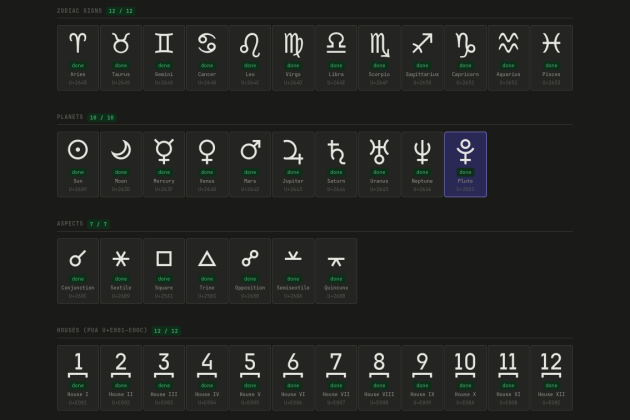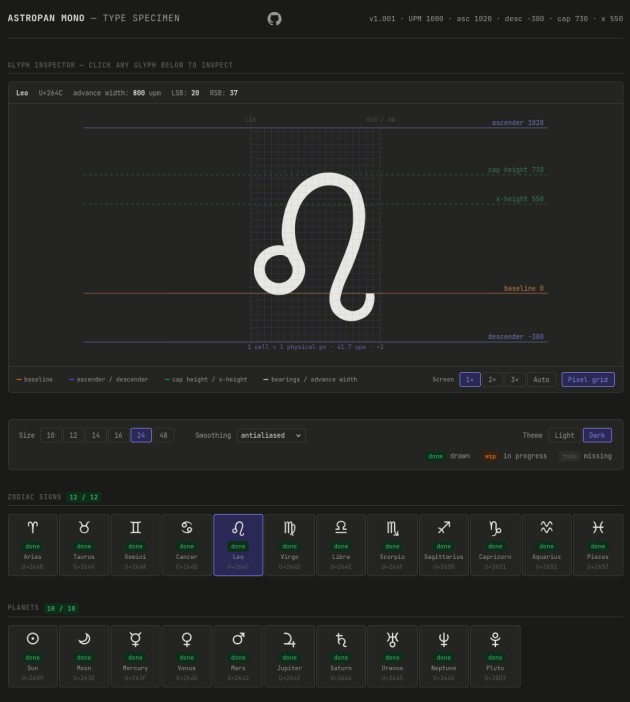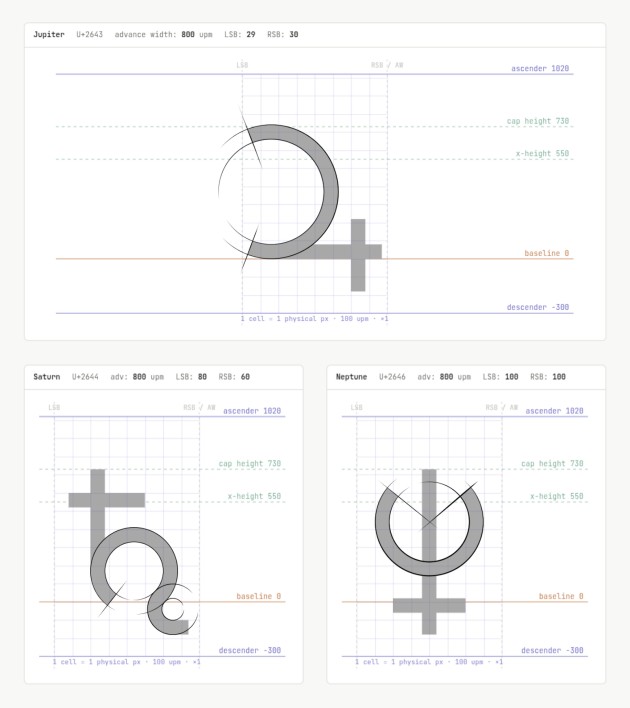
精美的AstroPan Mono神秘学字体素材,这是一款专为占星软件、界面和神秘学项目设计的图标字体。即使在小尺寸(低至 10 像素)下也能保持极佳的清晰度,并严格遵循等宽网格。
这款字体的设计灵感源自 JetBrains Mono 的工程精度,并将高精度设计应用于占星图形的需求。
– 行星与相位:采用统一笔画粗细的精确几何形状。每个行星字形都基于一致的圆形基础构建。
–星座:采用书法风格,并经过精心的手动光学补偿,以确保在 800 单位等宽空间内具有完美的辨识度。
– 主笔画宽度:800 UPM – 主笔画:80 UPM – 细笔画:50 UPM – 针对 10px 及以上尺寸进行了优化
重要提示:这是一款纯符号字体(Unicode 映射)。它不包含拉丁字符或数字。